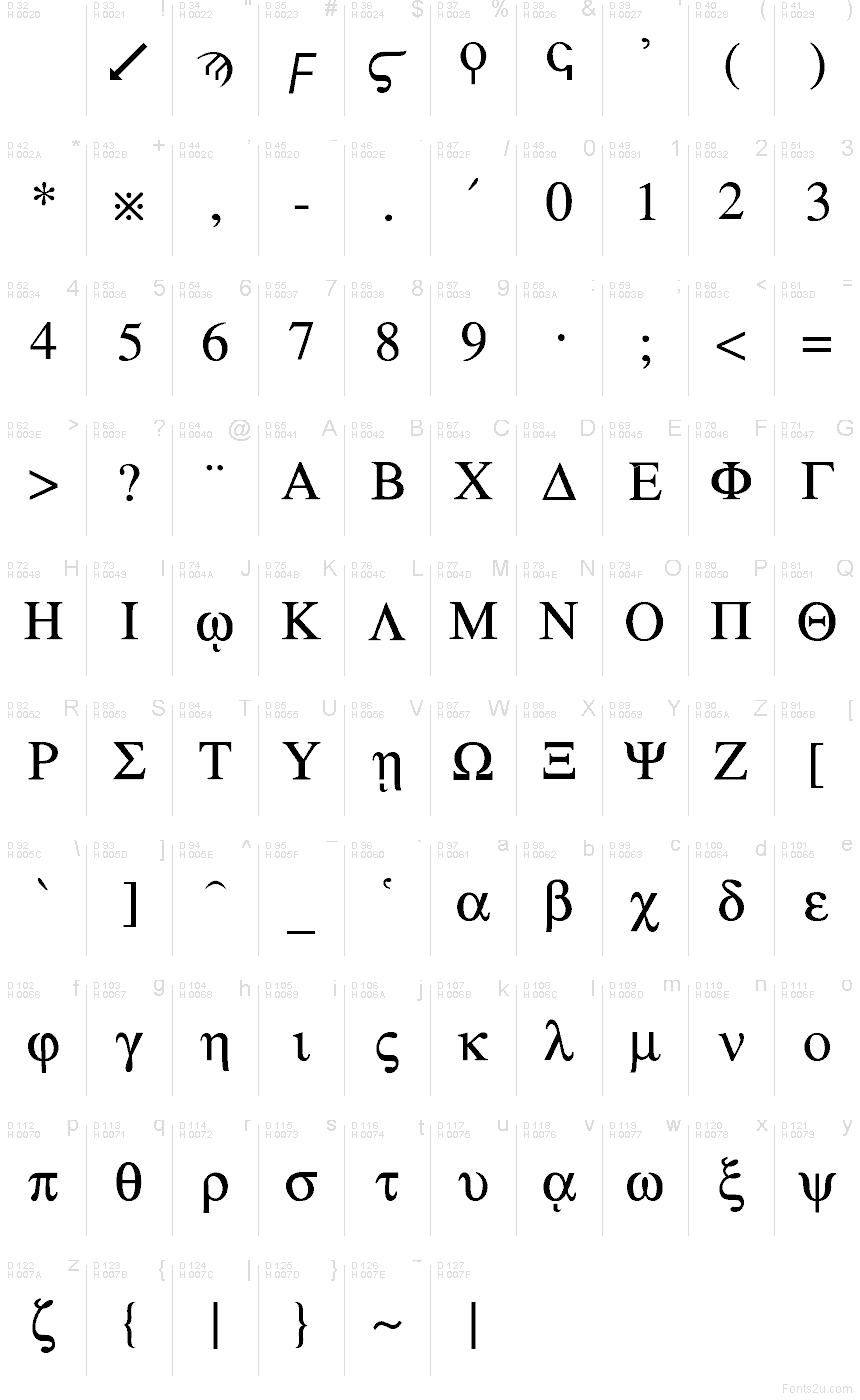
Grego1
Grego 1, uma fonte gratuita de estilo grego criada por A. M. Fountain e P. J. Gentry, inspira-se em inscrições clássicas e formas de manuscritos, em vez das formas latinas comuns. O seu ritmo resulta de traços verticais altos, curvas abertas e alguns descendentes profundos que conferem à tipografia um tom formal, porém ligeiramente arcaico.
Esse caráter torna a Grego 1 uma escolha natural para cartazes mitológicos, gráficos de museus, títulos de jogos históricos, capas de livros e menus de restaurantes temáticos. A combinação da estrutura que remete à escultura com a suavidade do movimento manual também é perfeita para aberturas de capítulos, títulos de eventos ou embalagens que desejam uma referência direta ao Mediterrâneo ou ao mundo antigo.